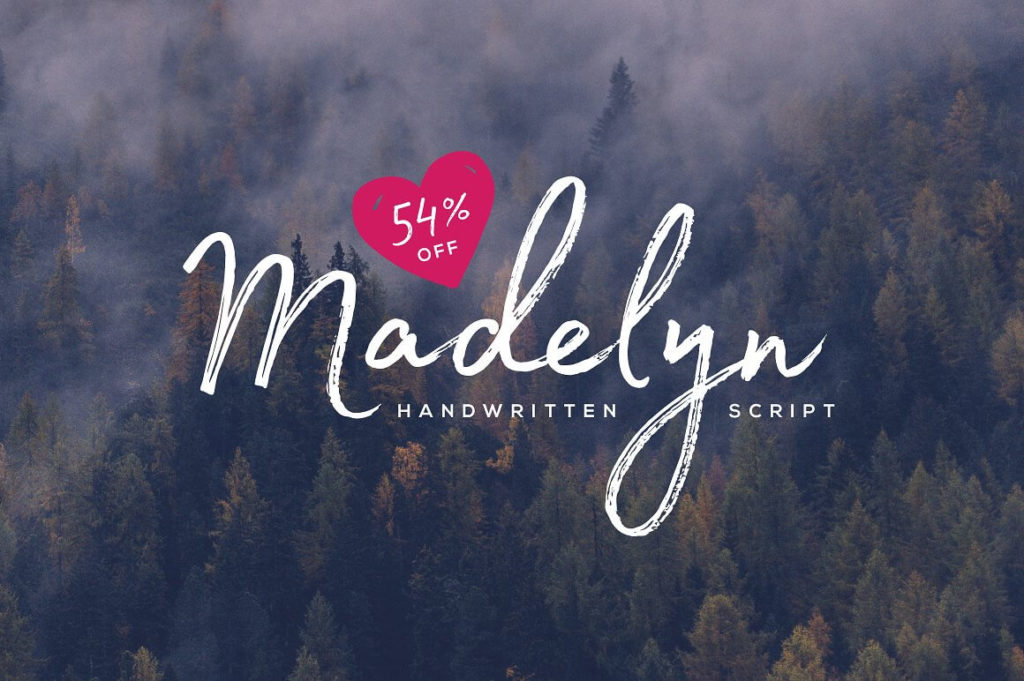
Шрифт Madelyn Script
это элегантный рукописный шрифт в стиле современной каллиграфии, изначально разработанный студией Embuntype (2020 г.). Кириллическая версия адаптирована для комфортного набора текстов на русском языке, сохраняя плавные линии, характерные лигатуры и выразительные альтернативы оригинала. Шрифт отличается утончённым, «дорогим» характером и хорошо подходит для создания приглашений, упаковки, логотипов и акцидентных заголовков. Скачать бесплатно кириллическую версию можно по ссылке ниже (лицензию уточняйте перед коммерческим использованием)